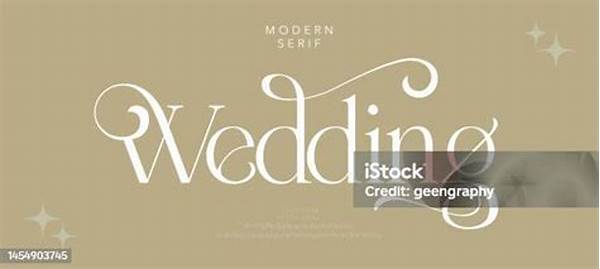
Hai, Sobat! Jika kamu sedang merencanakan sebuah pernikahan mewah, pasti banyak hal yang perlu dipersiapkan. Tapi, pernahkah kamu berpikir tentang font yang akan digunakan dalam undangan atau dekorasi pernikahanmu? Percaya atau tidak, memilih font yang tepat bisa memberi sentuhan istimewa pada keseluruhan acara. Font artistik untuk pernikahan mewah bukan hanya soal estetika, tetapi juga cara menyampaikan tema dan suasana yang ingin kamu hadirkan.
Mengapa Memilih Font Artistik untuk Pernikahan Mewah?
Pernikahan adalah momen spesial yang dirayakan sekali seumur hidup. Jadi, setiap detailnya harus diperhatikan, termasuk pilihan font. Font artistik untuk pernikahan mewah tidak hanya memberikan kesan elegan, tetapi juga menunjukkan kepribadian pasangan. Bayangkan sebuah undangan dengan huruf biasa saja, tentu tidak akan meninggalkan kesan yang mendalam seperti jika kamu memilih font dengan gaya yang artistik dan mewah.
Pastinya, kamu ingin undangan pernikahanmu menjadi sebuah karya seni yang dikenang oleh para tamu. Ada banyak sekali opsi font artistik untuk pernikahan mewah di luar sana, mulai dari yang berbentuk klasik seperti kaligrafi hingga yang lebih modern dengan sentuhan kontemporer. Setiap jenis font bisa menciptakan suasana yang berbeda, dan inilah yang membuat pemilihan font menjadi sangat penting dalam perencanaan pernikahan mewahmu.
Lebih dari sekedar elemen desain, font juga bisa mempengaruhi bagaimana tamu merespons undanganmu. Font yang tepat bisa menyampaikan pesan cinta yang tulus dan elegan. Jadi, luangkan waktu untuk memilih font artistik untuk pernikahan mewah agar bisa menciptakan kesan yang sempurna.
Inspirasi Font Artistik untuk Pernikahan Mewah
1. Kaligrafi Klasik: Menghadirkan kesan elegan dan tradisional. Font ini cocok untuk pasangan yang ingin pernikahan mereka terasa timeless.
2. Font Modern: Pilihan yang tepat untuk pernikahan dengan tema kontemporer. Font ini menambahkan sentuhan segar dan inovatif pada desain undangan.
3. Handwritten Fonts: Memberikan kesan personal dan intim. Font ini membuat undangan seolah-olah ditulis tangan khusus untuk tamu.
4. Serif Elegan: Cocok untuk mereka yang menyukai tampilan yang bersih dan rapi. Font ini memberikan nuansa formal namun tetap dekat.
5. Brush Script: Menghadirkan kesan artistik dan berkelas, seolah-olah dicetak dengan kuas kuas yang mewah. Cocok untuk pernikahan dengan tema artistic yang kuat.
Bagaimana Memilih Font Artistik yang Tepat?
Memilih font artistik untuk pernikahan mewah bisa menjadi tantangan tersendiri. Pertama, tentukan tema keseluruhan dari pernikahan. Apakah kamu menginginkan suasana vintage, modern, atau mungkin campuran keduanya? Mengetahui tema besar akan membantumu mempersempit pilihan font yang sesuai.
Setelah itu, selalu lakukan pengecekan dengan menggunakannya dalam kata-kata yang akan dicetak dalam undangan. Beberapa font terlihat indah secara teori, namun saat diaplikasikan tidak selalu cocok dengan kata-kata dalam undanganmu. Cobalah beberapa opsi font dan lihat mana yang benar-benar terasa paling pas.
Jangan lupa juga untuk mempertimbangkan readability atau keterbacaan. Sebuah font artistik mungkin terlihat menawan, tetapi jika sulit dibaca, maka tidak akan efektif. Pastikan tamumu bisa membaca informasi penting seperti tanggal dan lokasi tanpa kebingungan, agar esensi informasi dalam undangan bisa sampai dengan tepat.
Tips Menggunakan Font Artistik dalam Dekorasi
Font artistik tidak hanya untuk undangan. Kamu juga bisa memanfaatkannya dalam berbagai elemen dekorasi pernikahan. Misalnya, menu makan malam, papan petunjuk, hingga nama meja. Dengan memilih font yang seragam, kamu bisa menciptakan kesan konsisten di seluruh acara.
Selain itu, memilih palet warna yang sesuai dengan font akan memperkuat tema dan suasana. Untuk pernikahan mewah, warna emas atau perak seringkali menjadi pilihan yang aman. Kombinasi antara font artistik dan warna yang tepat akan membuat dekorasi terlihat semakin sempurna.
Dan jangan lupa, konsultasikan dengan desainer atau pihak dekorasi yang mengerti tentang estetika font. Mereka bisa membantu memilih dan menyelaraskan font artistik untuk pernikahan mewahmu agar semuanya berjalan dengan harmonis. Jadi, persiapkan semuanya dengan seksama dan biarkan font artistik membawamu menuju pernikahan impian.
Kiat Praktis Menerapkan Font Artistik
Setelah mengetahui pentingnya font artistik, berikut adalah beberapa kiat praktis untuk menerapkannya:
1. Uji Coba: Sebelum final, coba cetak beberapa undangan untuk melihat hasil akhirnya.
2. Pertimbangkan Anggaran: Beberapa font mungkin memerlukan lisensi atau biaya tambahan.
3. Kombinasi Warna: Pilih warna font yang kontras dengan background agar mudah dibaca.
4. Minimalis adalah Kunci: Jangan tambahkan terlalu banyak elemen dalam desain agar tetap fokus.
5. Feedback: Minta pendapat dari teman apakah font mudah dibaca dan sesuai tema.
Dan, pada akhirnya, jadikan font artistik sebagai bagian dari cerita cinta kalian. Sebuah pernikahan adalah awal dari perjalanan yang panjang, dan font yang kamu pilih bisa menjadi simbol awal dari komitmen dalam hubungan kalian. Semoga artikel ini bisa membantu dan memberikan inspirasi dalam memilih font artistik untuk pernikahan mewah yang paling sesuai dengan impianmu.